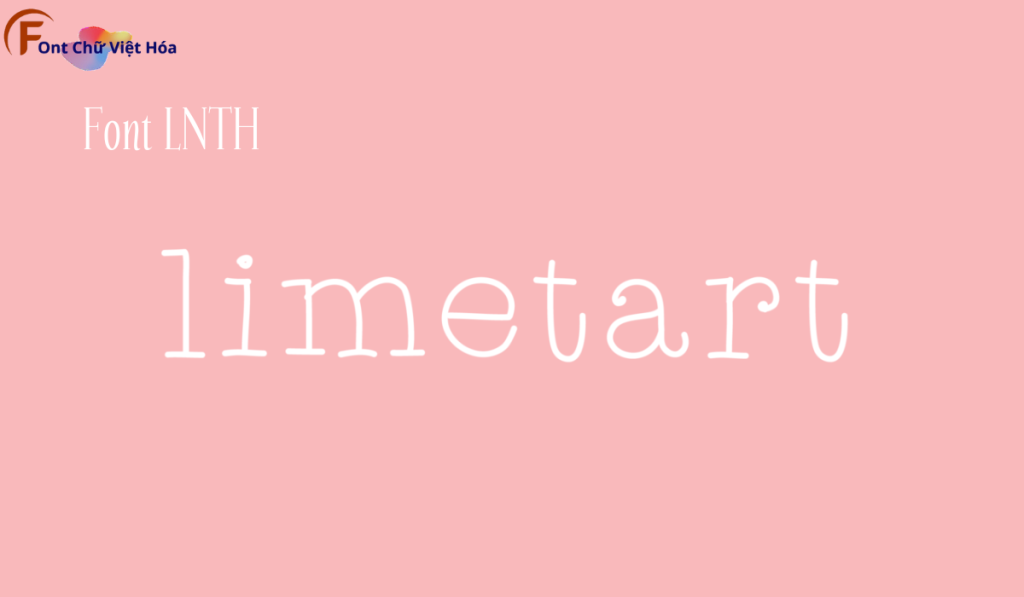
Font LNTH Limetart Việt Hóa
Font LNTH Limetart Việt Hóa là một font chữ vui nhộn, thuộc bộ LNTH, với thiết kế tươi sáng và năng động. Phong cách của font này phù hợp với các dự án thiết kế cần sự vui tươi và sáng tạo, như poster, thiệp mời, hoặc bảng hiệu. Font LNTH Limetart Việt Hóa mang đến sự vui nhộn và dễ nhận diện, ứng dụng trong các lĩnh vực sáng tạo. Đặc điểm hình dạng của font bao gồm các đường nét mềm mại và tươi sáng, giúp tăng tính thẩm mỹ và sự chú ý. Việc Việt hóa font giúp người dùng dễ dàng sử dụng trong các thiết kế tiếng Việt, mang lại sự tiện lợi và linh hoạt.